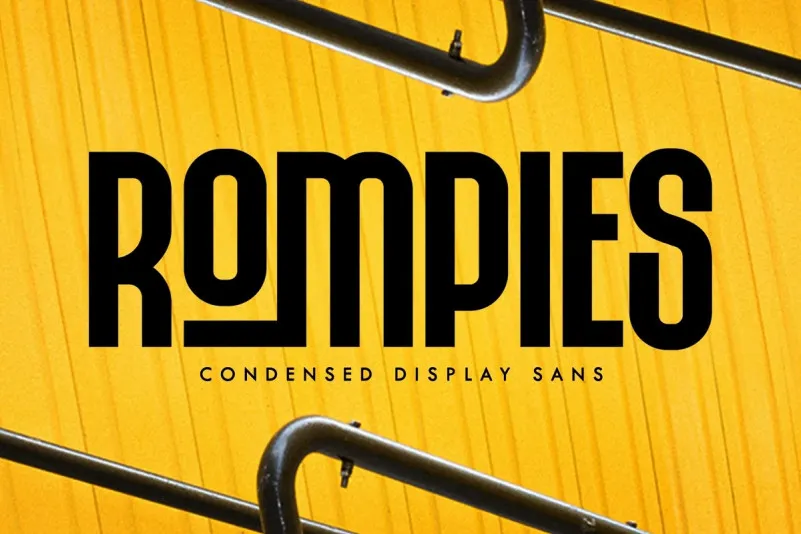
Rompies Font – Fonte Grátis
Rompies Font
A Rompies é uma fonte display surpreendentemente única e intrigante. Arterfak Project projetou-a com destreza, enfatizando a legibilidade e destacando as combinações únicas de formas alfabéticas através de traços finos em letras e espaçamento entre letras apertado. Esta fonte é um tipo todo maiúsculo que junta o alfabeto minúsculo com os caracteres maiúsculos, proporcionando flexibilidade ao mesmo tempo que diminui a quantidade negativa do espaço entre as letras. A Rompies é perfeita para criar texturas e elementos de design modernos, destacando-se em designs de marca ou layouts gráficos. Suas linhas finas criam um contrastes interessantes com os traços mais grossos, resultando em uma aparência vibrante e atraente. Seja você designer de logotipos, webdesigner, ilustrador ou qualquer profissional do design que busca adicionar algum toque único ao seu trabalho, a Rompies é um ótimo complemento para sua biblioteca de fontes.